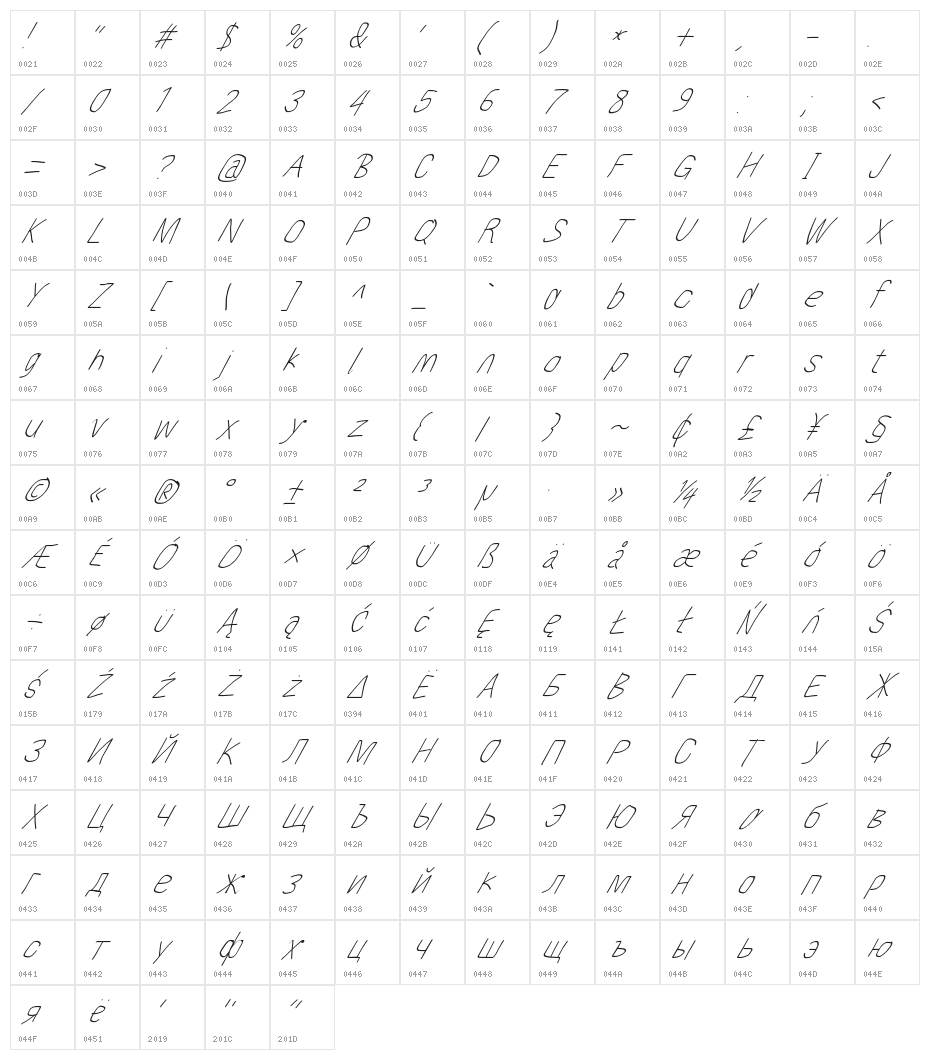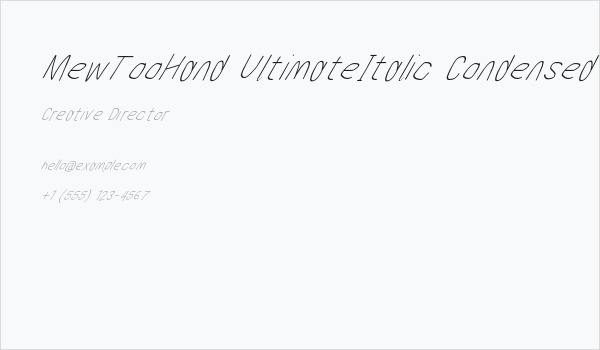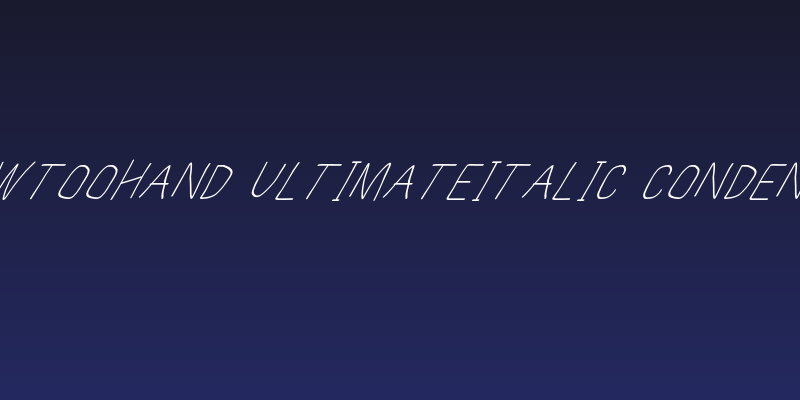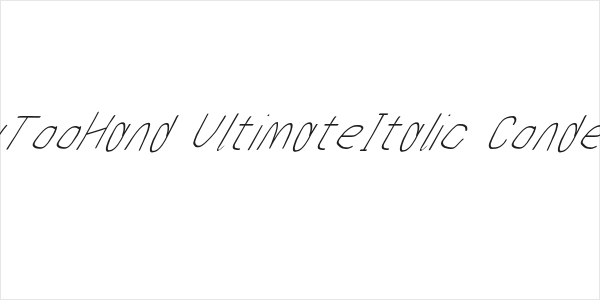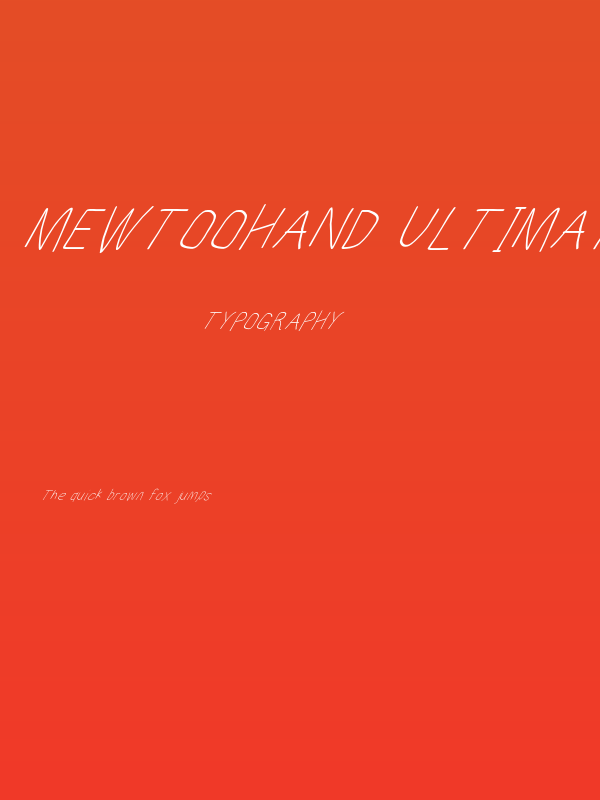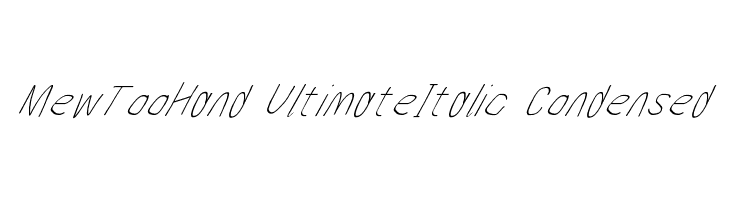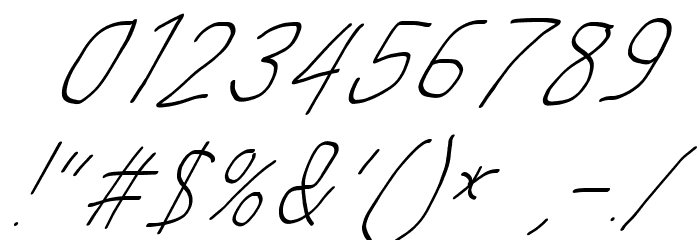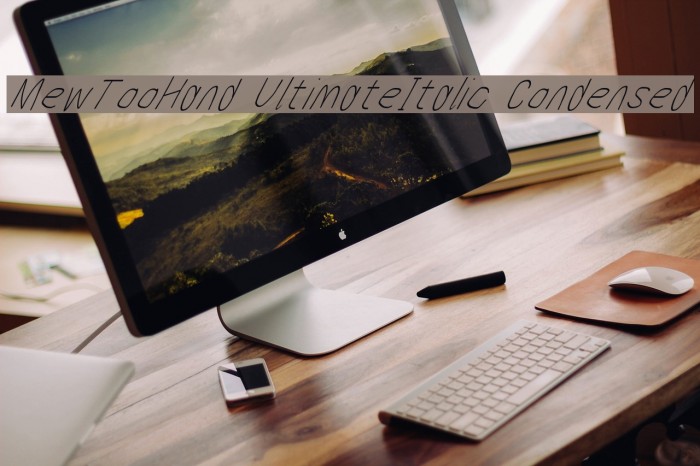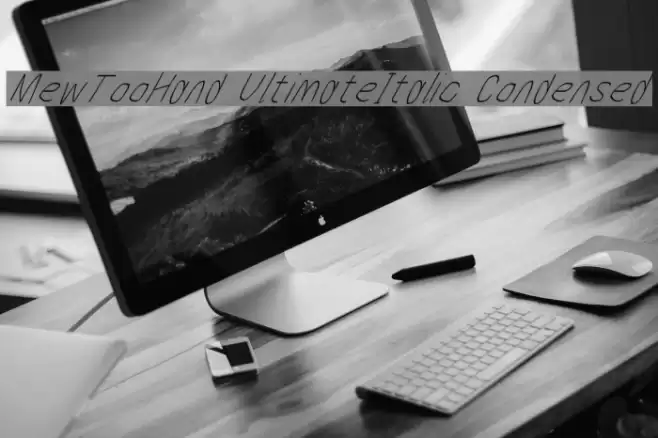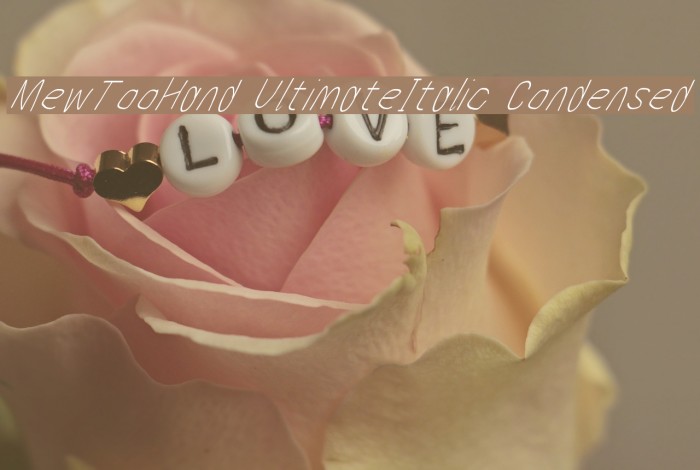
MewTooHand UltimateItalic Condensed Font
| Cas d'utilisation | Logos, Headlines, Creative projects |
| Projets proposés | Ideal for creative projects such as greeting cards, invitations, and personal branding. Its unique style is also suitable for logos and headlines that require a personal touch. |